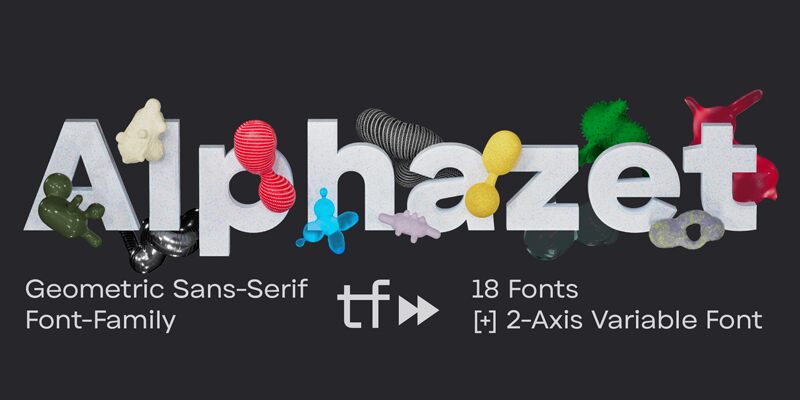
Alphazet Light
Alphazet Light, conçue par Type Forward, est une police sans empattement gratuite qui se définit par des lettres hautes et épurées ainsi qu'un rythme géométrique apaisant. Ses courbes arrondies et ses traits d'une grande netteté confèrent au design un aspect ouvert et aérien, tandis que la pointe des capitales ajoute juste ce qu'il faut de caractère pour éviter toute neutralité.
Cet équilibre fait d'Alphazet Light un choix naturel pour le branding, les affiches d'exposition, les titres, le packaging et les titres éditoriaux qui exigent une certaine légèreté tout en conservant une structure solide. Elle se prête également parfaitement aux textes d'en-tête de sites web et aux lookbooks, surtout lorsque ses larges courbes et ses verticales généreuses disposent de l'espace nécessaire pour s'exprimer.
Développée par Type Forward et Luboslav Boyanov, Alphazet se décline en 9 graisses (de Thin à Black), accompagnées de leurs italiques obliques. La famille complète est disponible en format variable.
Caractéristiques :
- Large prise en charge linguistique
- Fonctionnalités OpenType
- Espacement et crénage parfaitement équilibrés
Design et conception :
Alphazet repose sur des principes géométriques et est construite à partir de formes simples. Elle présente une hauteur d'x importante et des proportions stables. Les ascendantes et descendantes courtes ainsi qu'une répartition homogène des graisses définissent son style, qui fait l'impasse sur les détails décoratifs.